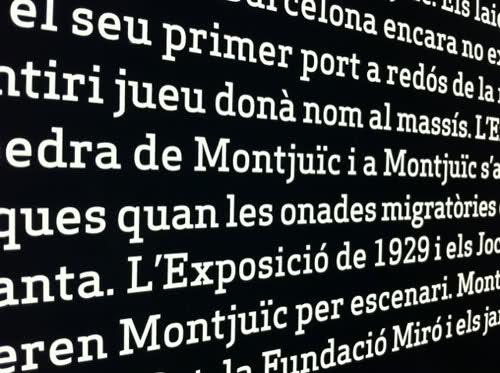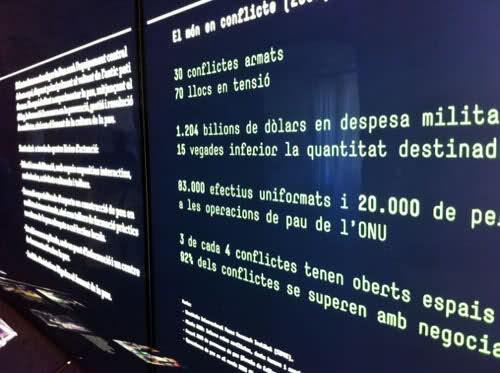
Welche Slab ist das?
diese wunderschöne Slab habe ich am Wochenende in Barcelona / Montjuic gefunden.
Jemand eine Idee, wie die Schrift heisst?
es scheint auch eine "serifenlose" version zu geben: